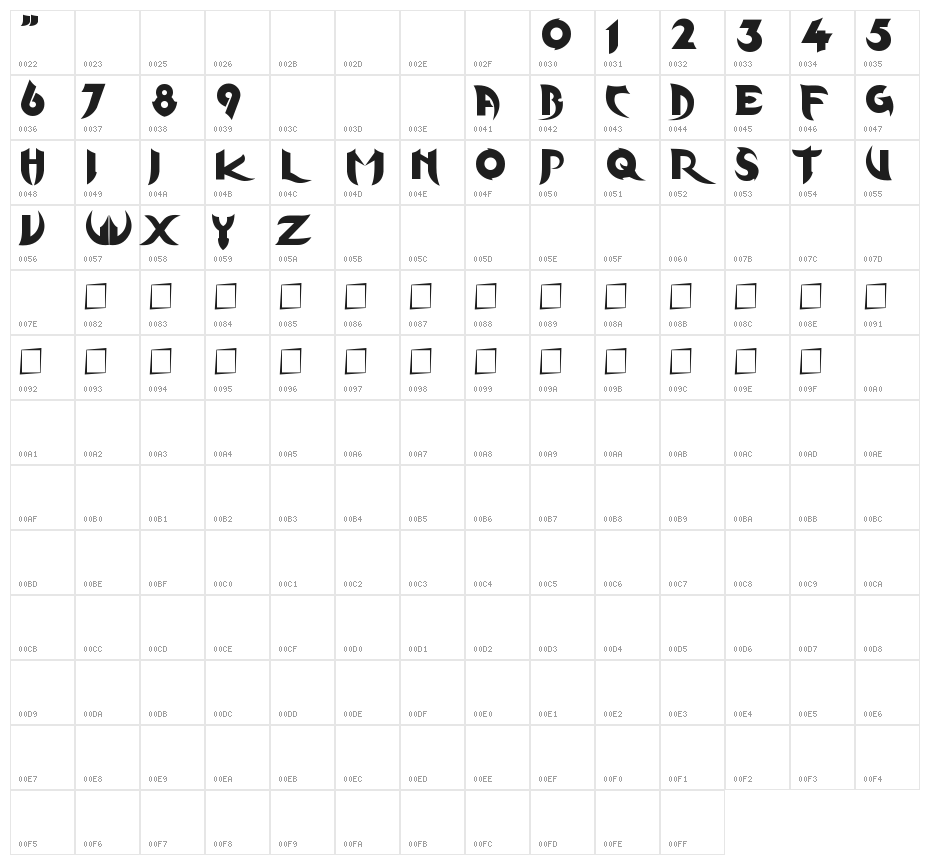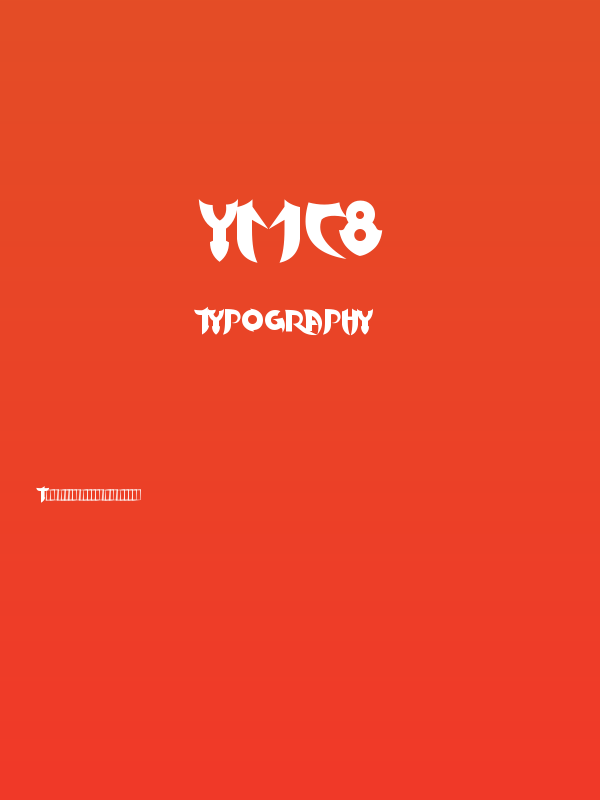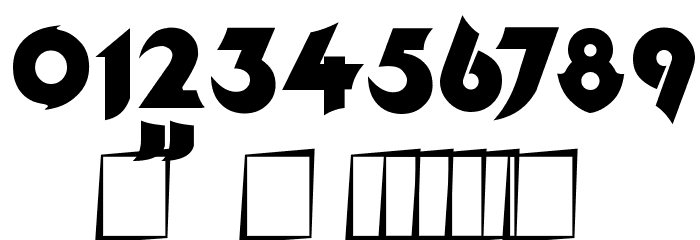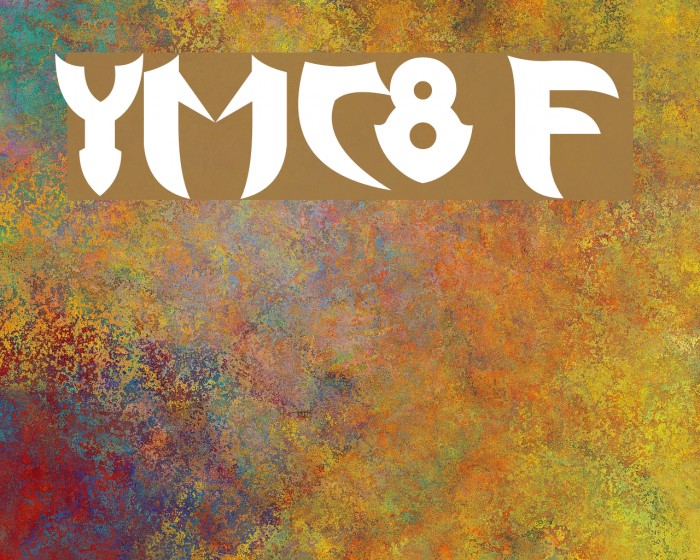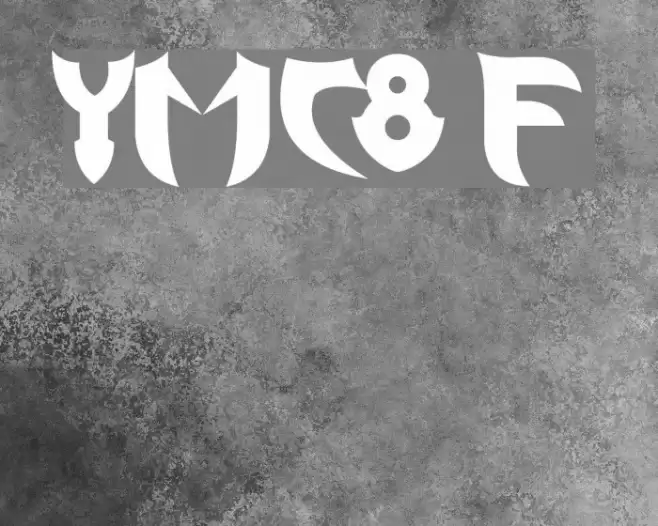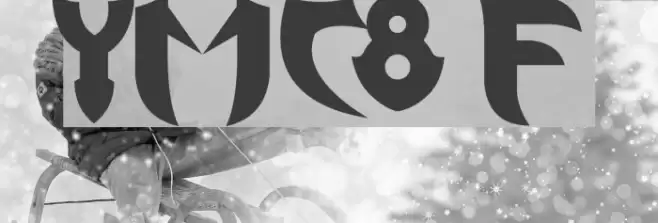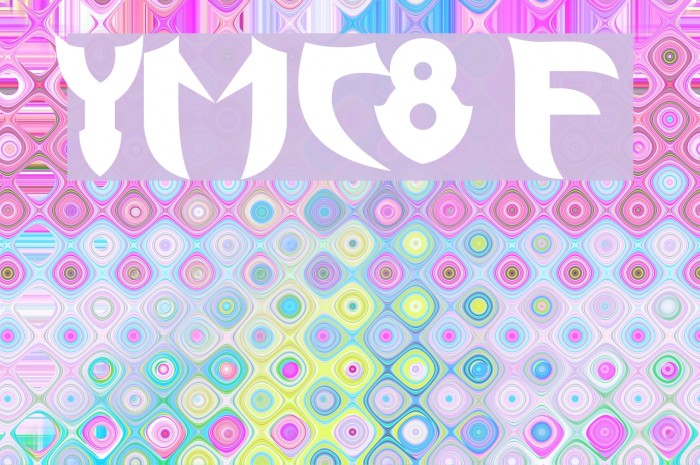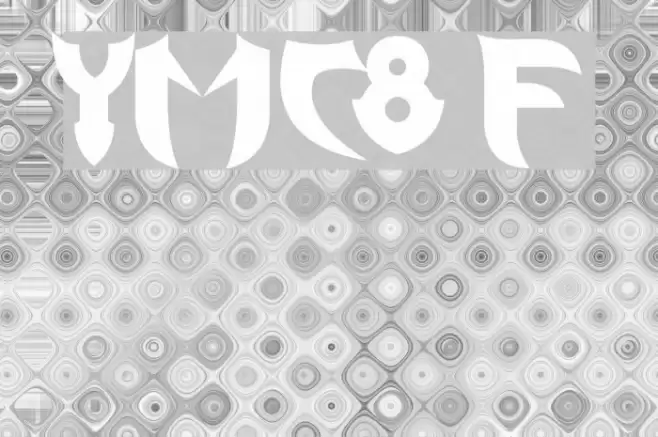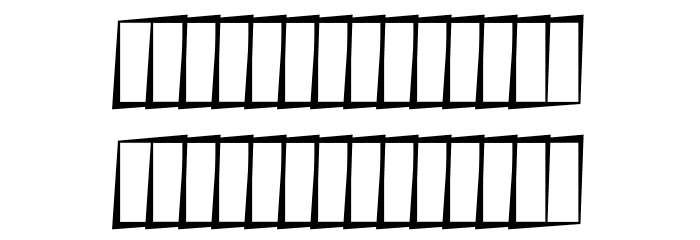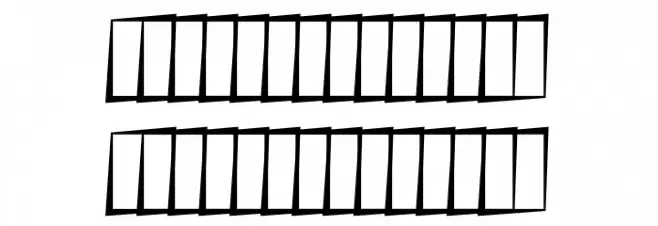
YMC8 Font
| Proiecte propuse | Ideal for sci-fi themed designs, video game titles, movie posters, and branding that requires a strong, modern impact. |